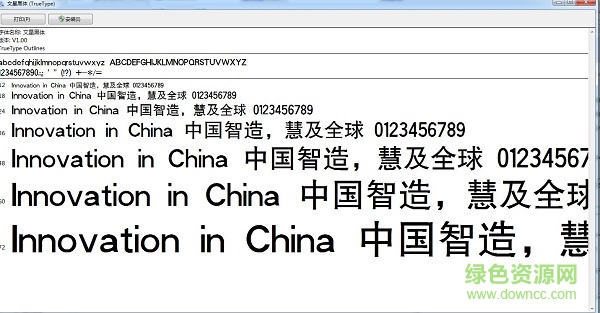
文星字體官方打包合集收錄了文星標宋、文星簡小標宋、文星簡美黑、文星仿宋字體、文星黑體、文星簡美黑、文星簡行楷等十幾款字體,適用范圍廣泛,有需要者快來綠色資源網(wǎng)免費下載吧!
【黑體字體】
黑體是機器印刷術(shù)的歷史產(chǎn)物。至少已有一百年的時間,黑體漢字抹掉了漢字手書體的一切人為印跡及其造字淵源,沒有手書的起始和收筆;
【隸書字體】
隸書基本是由篆書演化來的,主要將篆書圓轉(zhuǎn)的筆劃改為方折,因為在木簡上用漆寫字很難畫出圓轉(zhuǎn)的筆劃,所以隸書的書寫速度更快。
【仿宋字體】
顧名思義是宋體的變體,也是印刷體。印刷字體的一種,仿照宋版書上所刻的字體,筆畫粗細均勻,有長、方、扁三體。也叫仿宋體、仿宋字。